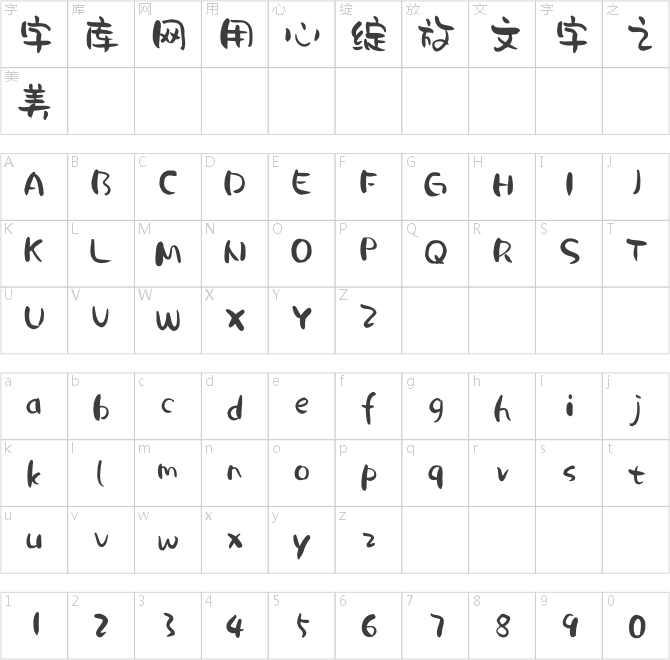
字体名称: 汉仪尚巍自由体
汉仪尚巍自由体
汉仪尚巍自由体介绍
汉仪尚巍自由体字体HYShangWeiZiYouTiW字库是一款让人赏心悦目、百看不厌的中文字体,适合各类广告和产品包装设计应用,字体大小8.86MB,格式为ttf字体,上传用户是︶低調^,作者/版权方为汉仪字库
汉仪尚巍自由体效果图